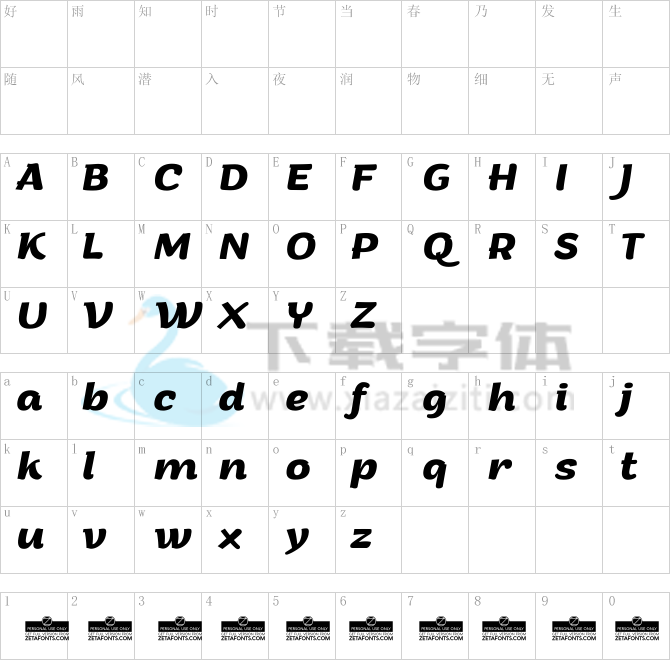
Arturo Trial.ttf字体下载,这款字体结构工整、笔画清晰,兼顾美观与易读性,适用于标题、正文、海报、包装、LOGO 等多种场景。字形优雅稳定,风格百搭耐看,适配日常排版与创意设计,让文字呈现更舒适、更具质感。Arturo Trial.ttf字体下载一笔一画,皆是细节,以均衡的比例、流畅的线条打造舒适视觉体验,字形端正大气,风格简约现代。无论是商业设计、品牌宣传还是日常排版,都能轻松驾驭,让文字更有格调与力量。Arturo Trial.ttf字体下载字体下载。